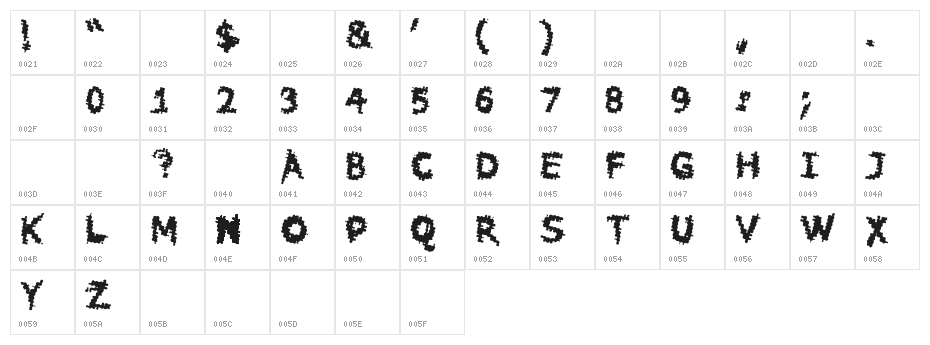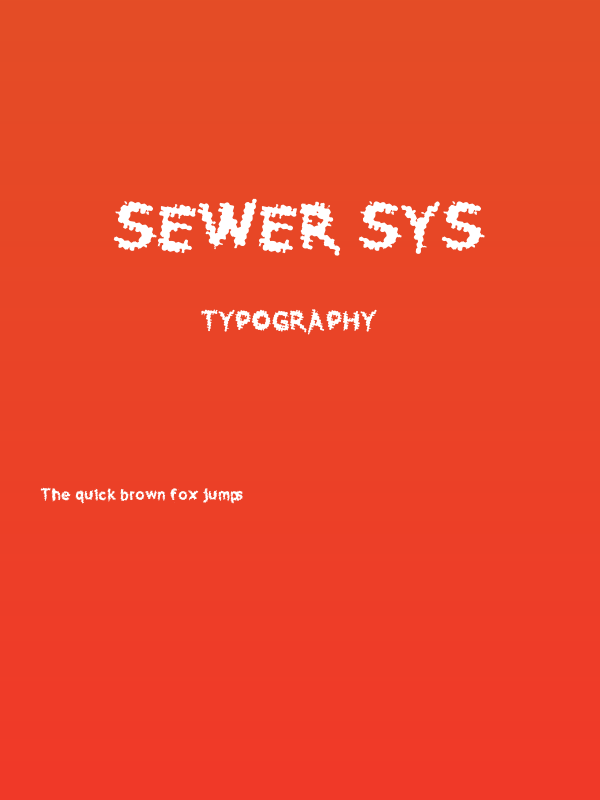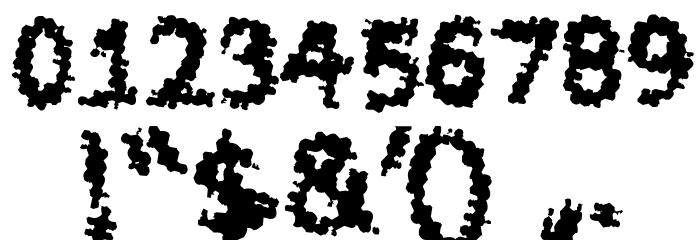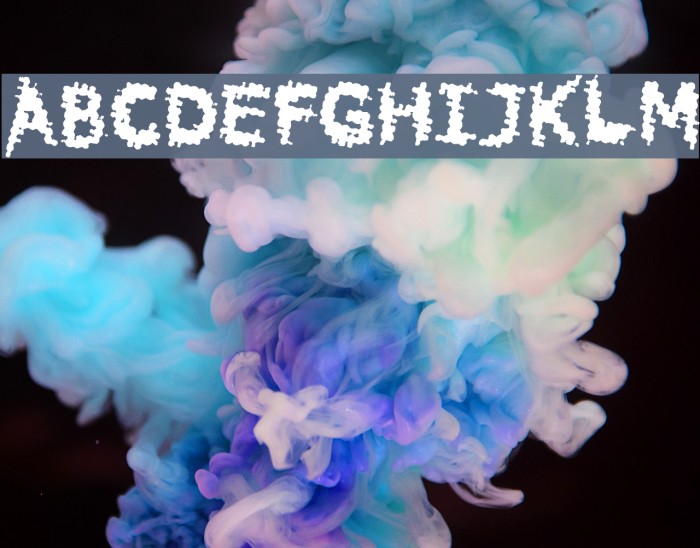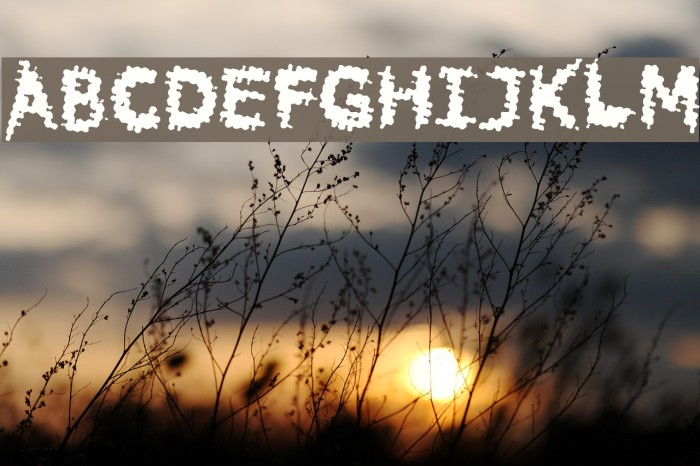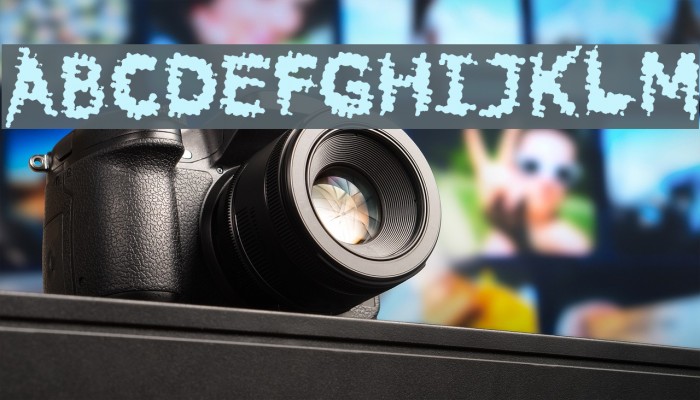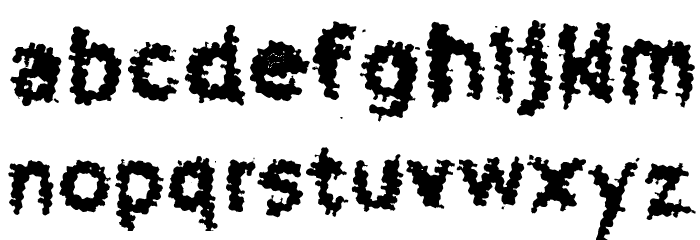
Sewer Sys Font
| Cas d'utilisation | Headlines, Logos, Artistic designs |
| Projets proposés | Ideal for artistic projects, album covers, posters, and any design requiring a bold, unconventional look. |